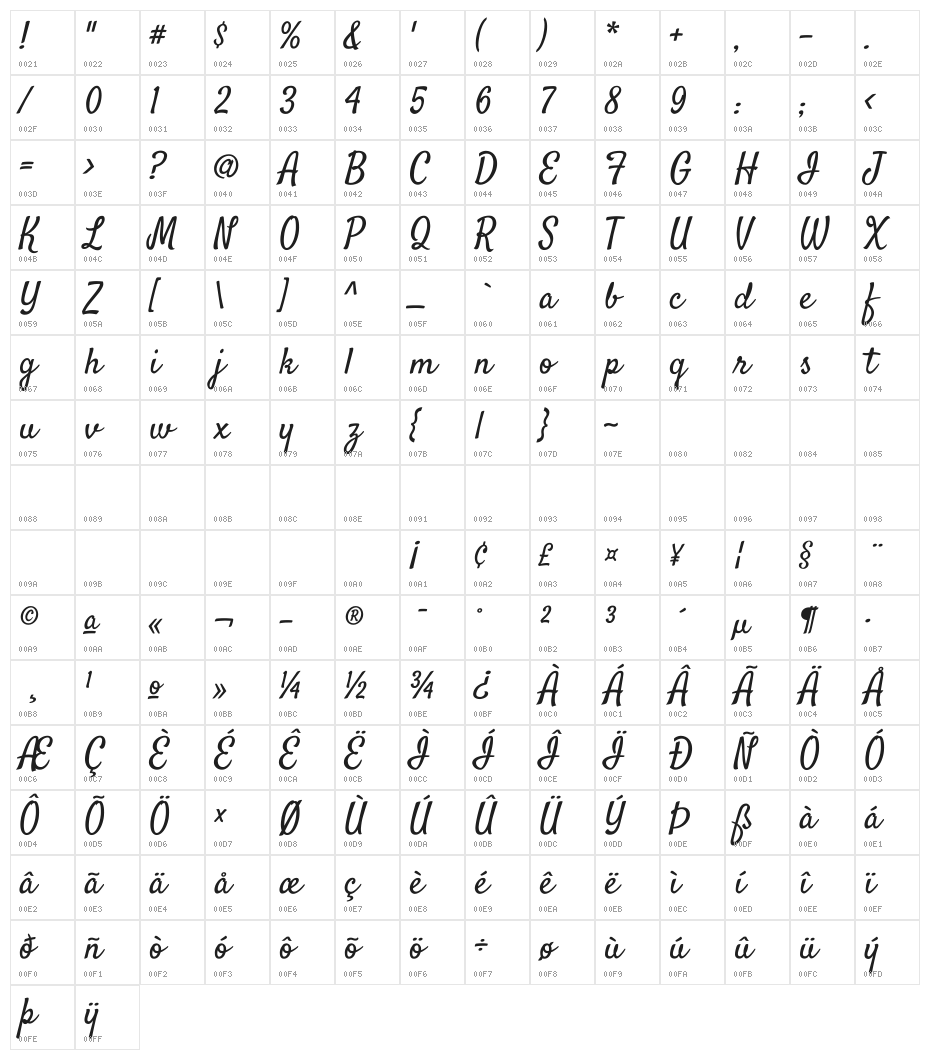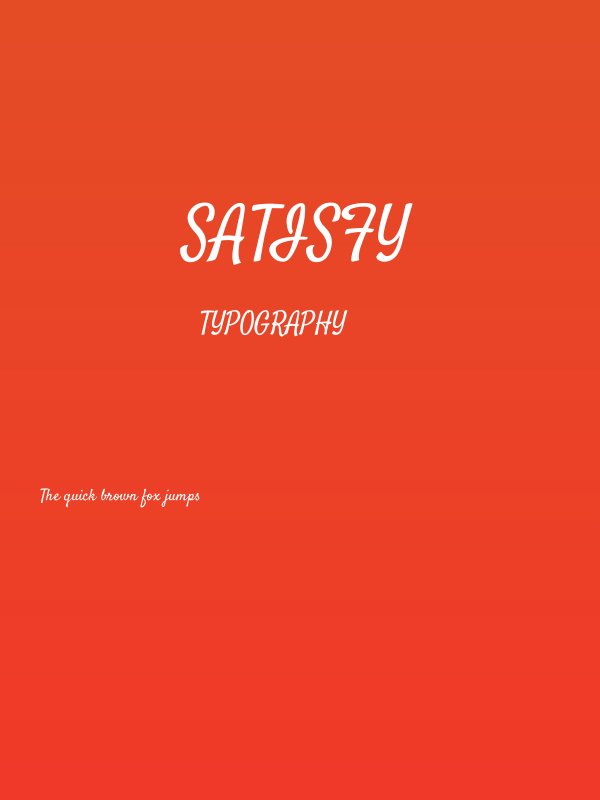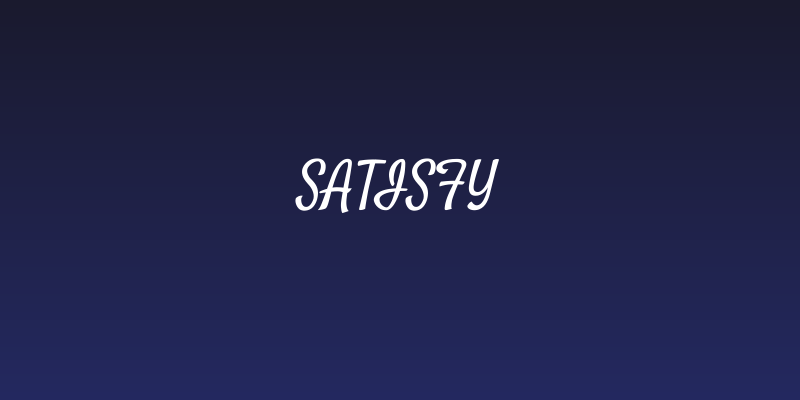
Satisfy Font
| Caso de uso | Logos, Headlines, Invitations |
| Proyectos propuestos | Ideal for wedding invitations, greeting cards, branding projects, and social media graphics. |
Satisfy